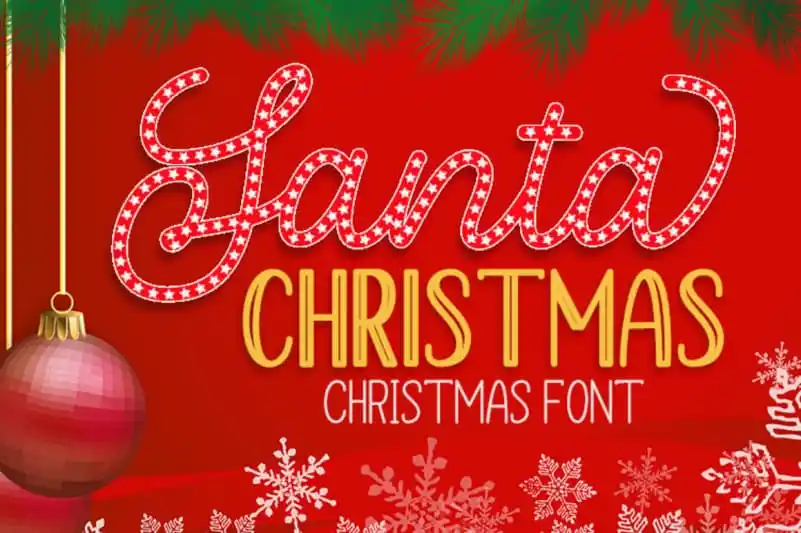
Santa Christmas – A Cute Holiday Font – Download Grátis
A Santa Christmas font é uma família exclusiva criada para o evento natalino, com padrões estrelados. Perfeita tanto para postagem em redes sociais quanto para projetos de impressão, esta fonte irá tornar seus trabalhos natalinos únicos e emocionantes. Com um design ideal para criação de t-shirts, design de arte em posters e até mesmo as publicações no Facebook ou Instagram durante a época festiva, a Santa Christmas font é uma escolha inteligente para qualquer designer que deseja criar algo especial neste tempo do ano. Além disso, a sua elegância com padrões estelares faz dela um recurso indispensável para qualquer projeto gráfico natalino que você possa querer realizar em breve.